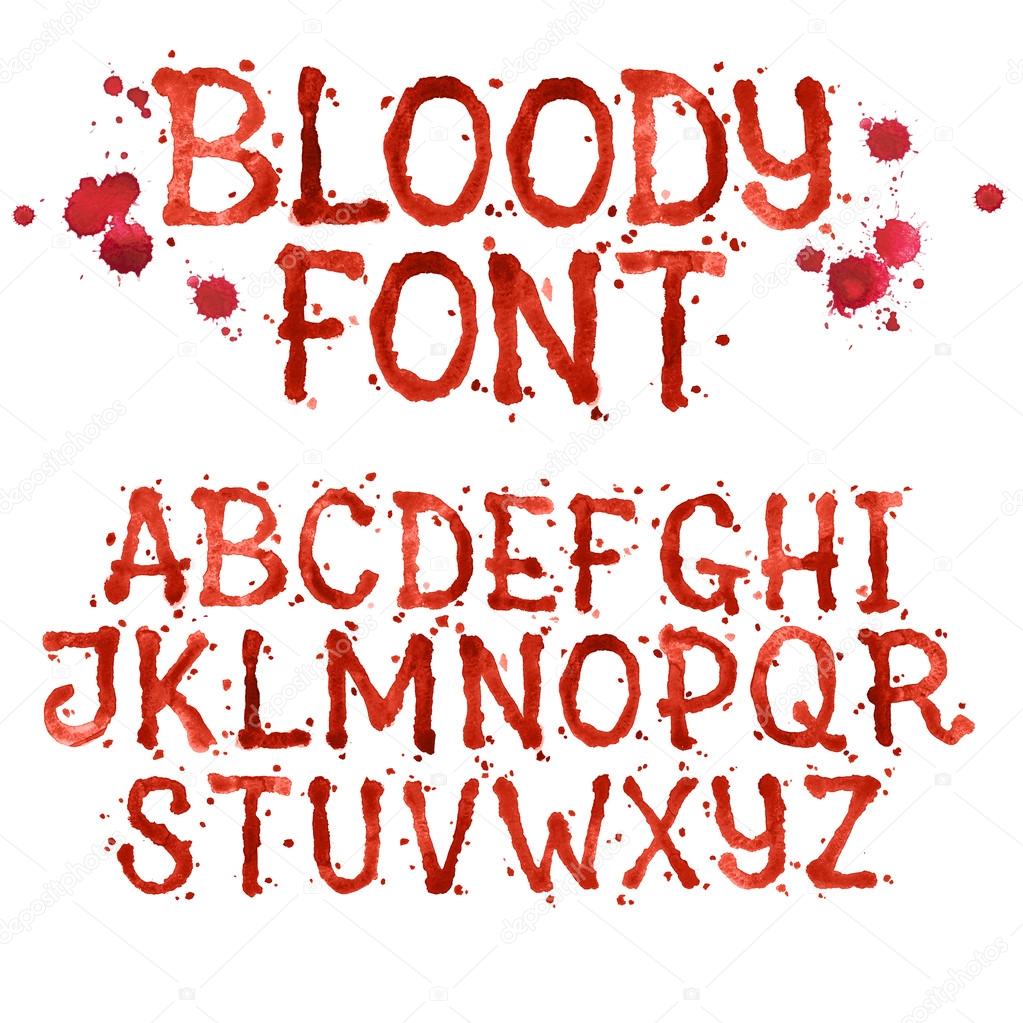
Кровь шрифты для фотошопа
Это интересно. Кровавые шрифты. Хотите создать кровавый текст? Это очень просто! Выбирайте подходящий шрифт и пишите свои зловещие послания и другие страшные надписи кровью.
Кровь, стекающая по символам, наводит на мрачные мысли. Тут же вспоминаются фильмы ужасов и ночные кошмары.За основу кровавого шрифта можно взять любой, чтобы затем «украсить» его в Photoshop.
Но лучше всего для этого подходят крупные шрифты без засечек.
Для фотошопа.Кровавый шрифт с поддержкой кириллицы (русский), а так же символов латинского алфавита и арабских цифр. В архиве два шрифта в формате TTF, стилизованных под кровавые потеки.
Сегодня я хочу предложить вам набор шрифтов кровь для фотошопа и других программ Windows, которые очень круто смотрятся на любой фотографии соответствующей тематики!
В голову приходит только мысль о каком нибудь кровавом шрифте, обтекающим кровью, каплями. В Paint e такое вряд ли возможно, в простом Word e тоже не найду подобный шрифт.
Набор шрифтов кровь для фотошопа и других программ Windows, которые очень круто смотрятся на любой фотографии соответствующей тематики!
Шрифт Blood Cyrillic обычного начертания, в стиле стекающей крови. Данный шрифт был использован при создании аватарки для группы, и загружен с целью дополнения к ней. Возможно вас заинтересует? Плагин для Фотошоп — Red.
Blood Blocks — Кровавый Death Metal Шрифт
Блочный жирный шрифт с брызгами и подтеками крови или краски, высокое разрешение. Включает расширенный Латинский (Английский) алфавит и цифры. Бесплатный для любого использования. Ссылка на сайт автора приветствуется. Создано: Июнь 2015
Сочинения достаточно для Хэллоуина, чтобы быть немного пугающим, но все же полностью читаемым.
Вы можете использовать этот бесплатный шрифт Хэллоуина для создания не только жуткого текста, но и тематических букв и символов.